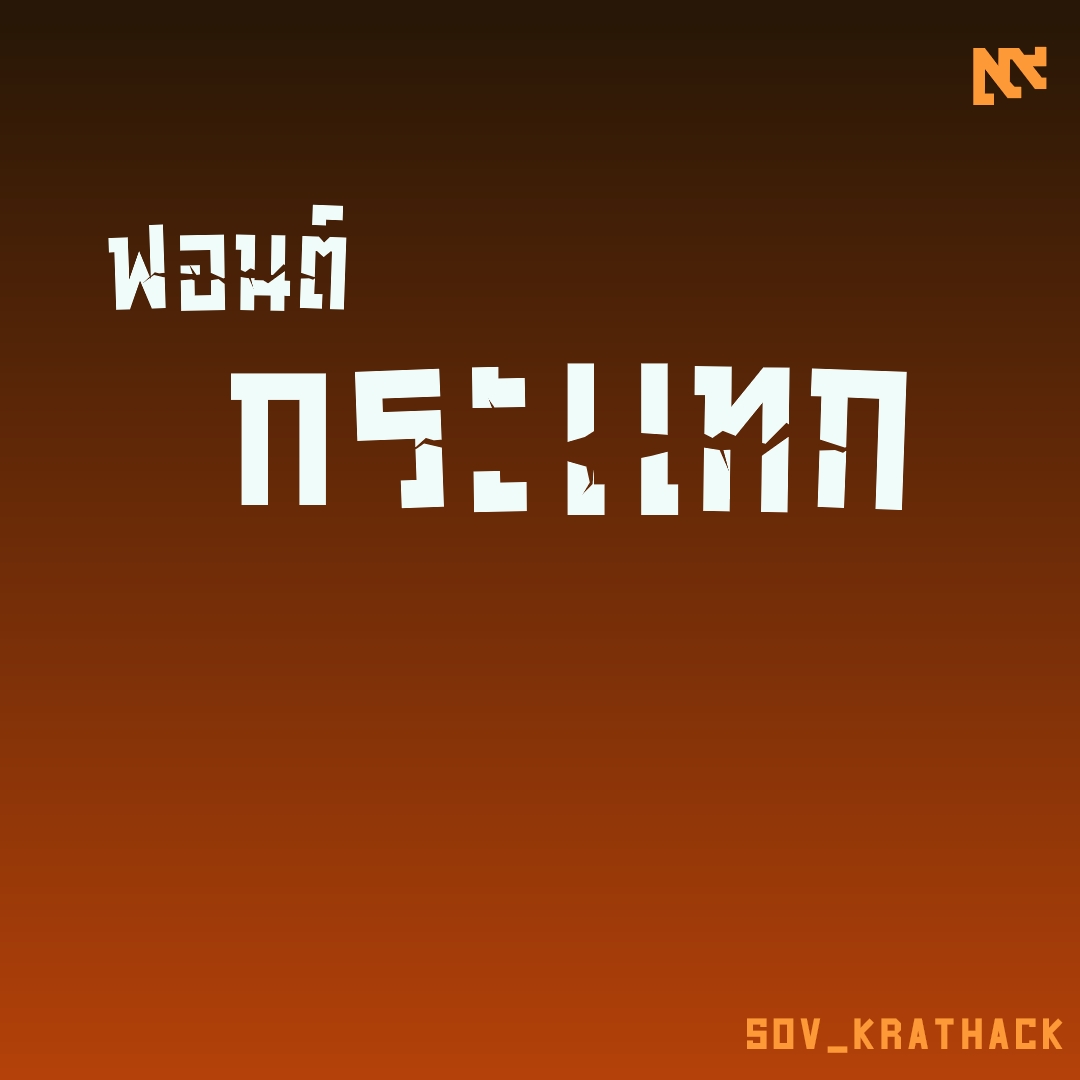
ฟอนต์ กระแทก
ฟอนต์กระแทก ใช้ ฯฯ หน้าอักษรที่อยากให้ถูกกระแทก แตกได้ 1-5 ตัวอักษร
ชื่อฟอนต์ : กระแทก
ฟอนต์กระแทก ใช้ ฯฯ หน้าอักษรที่อยากให้ถูกกระแทก แตกได้ 1-5 ตัวอักษร